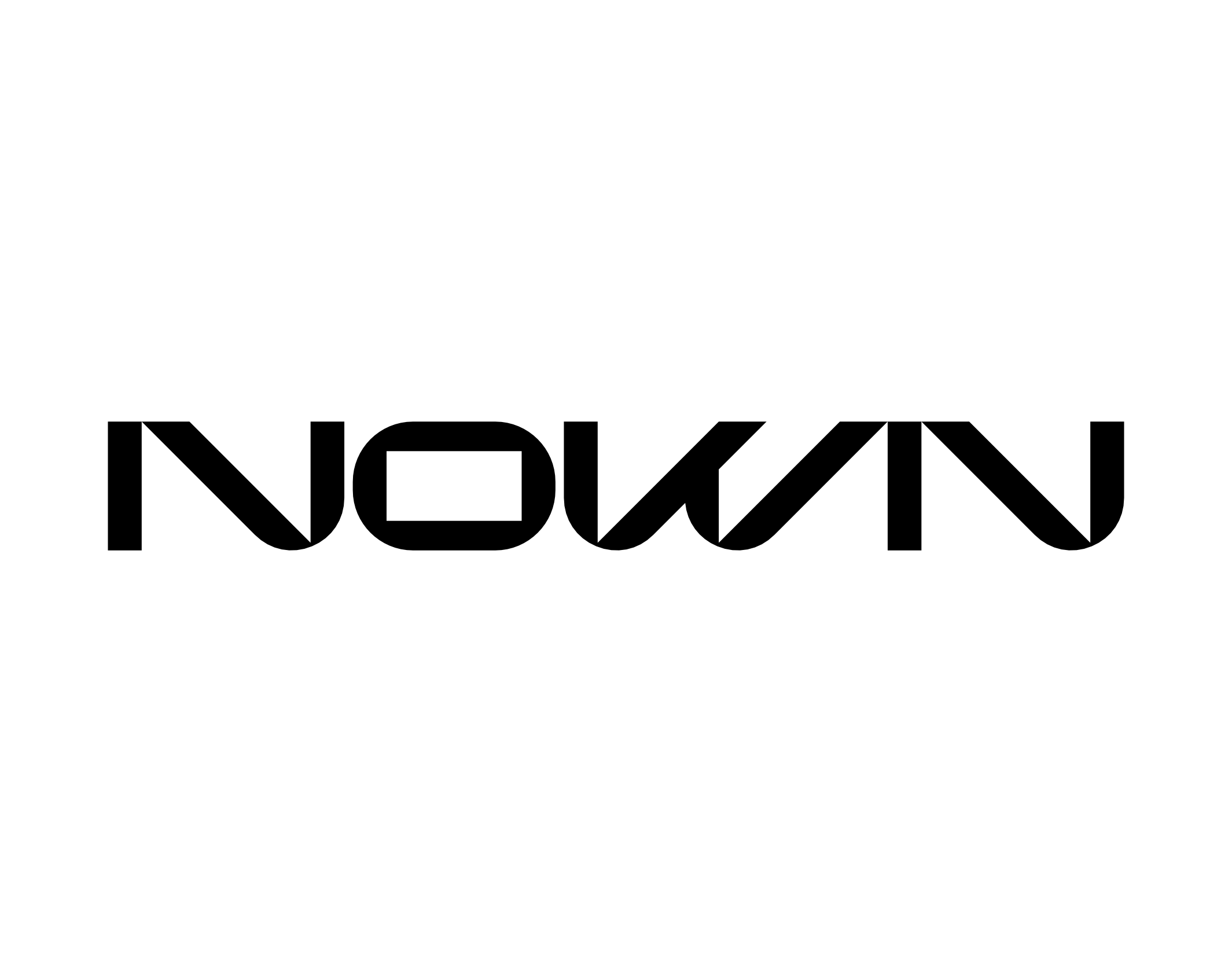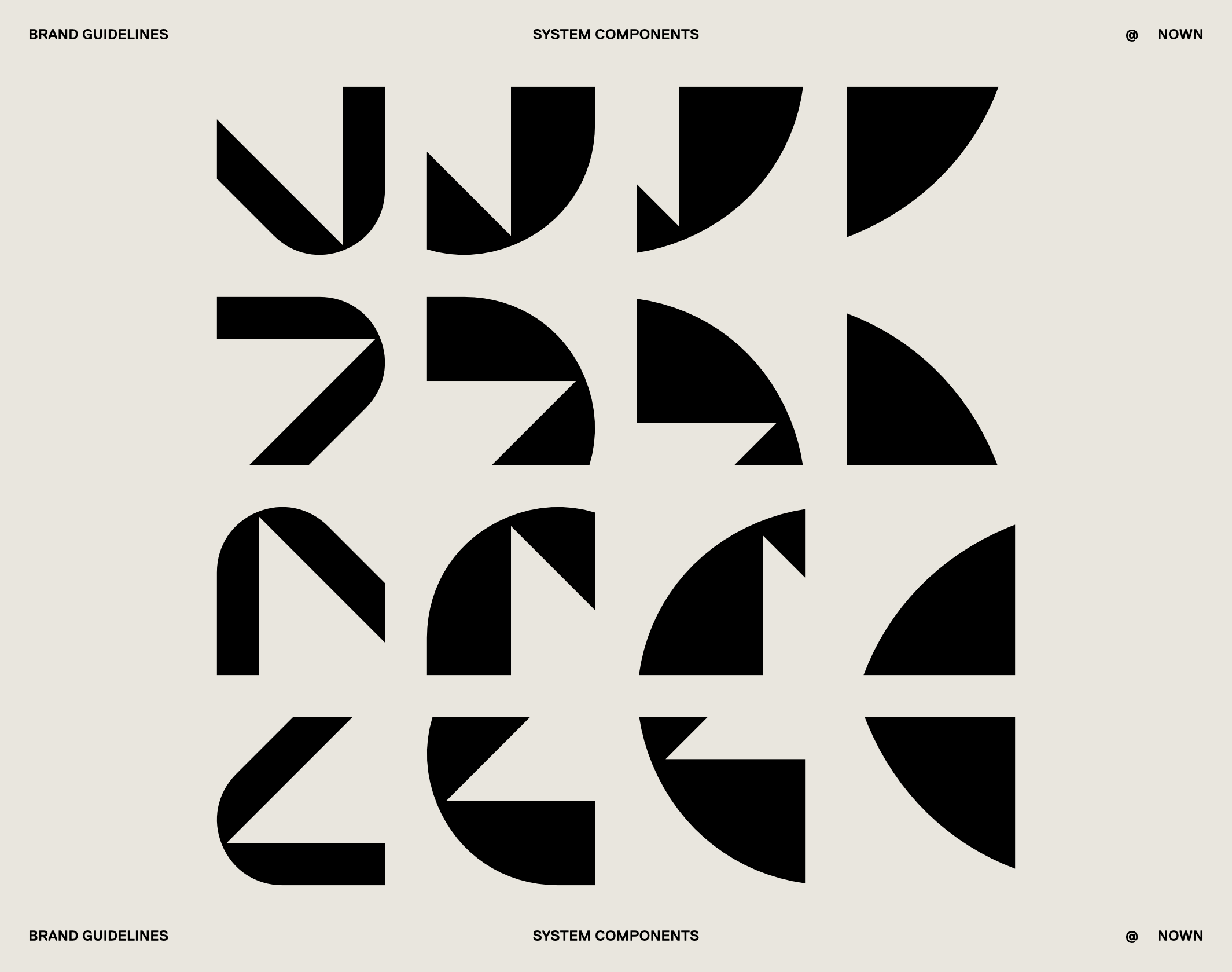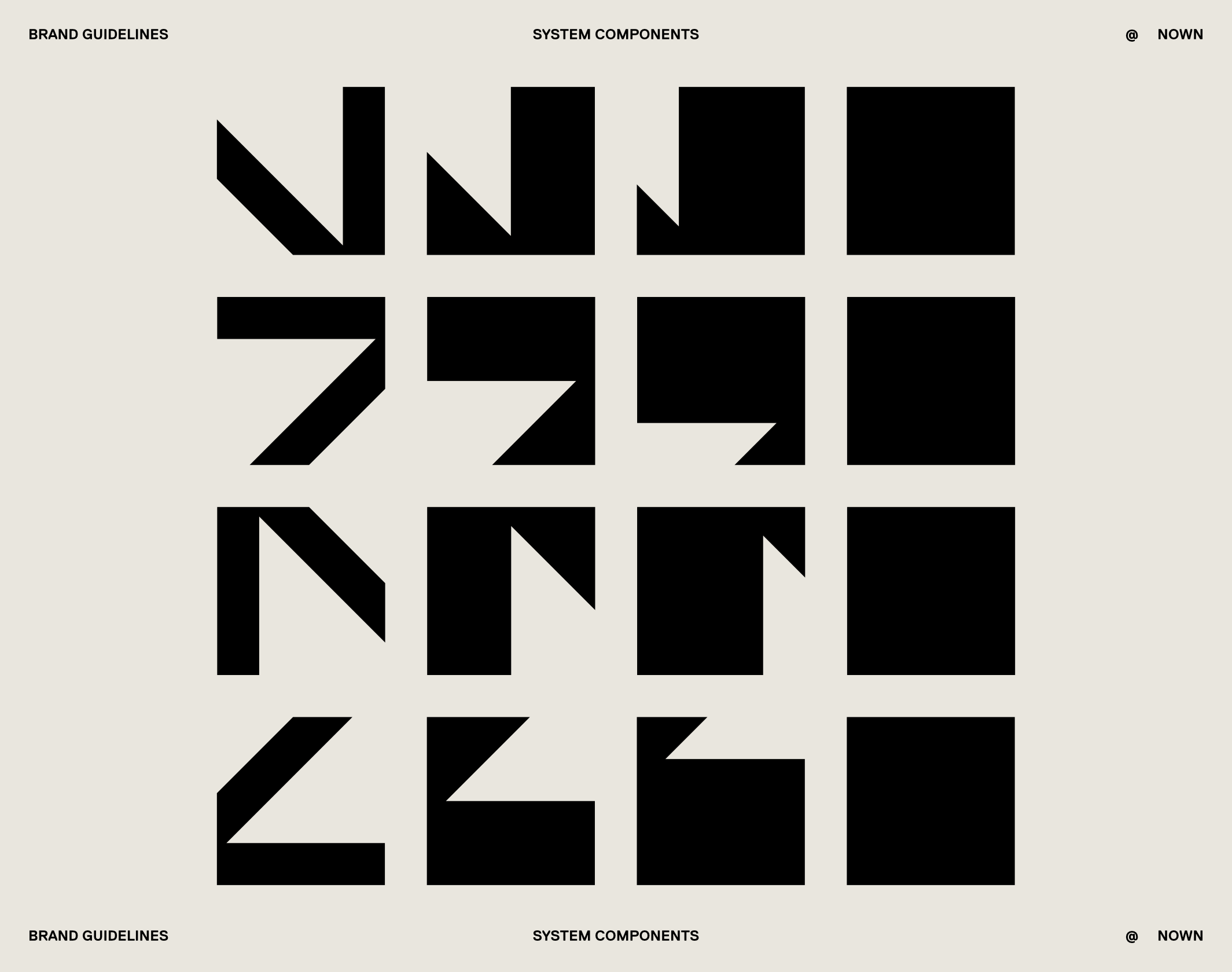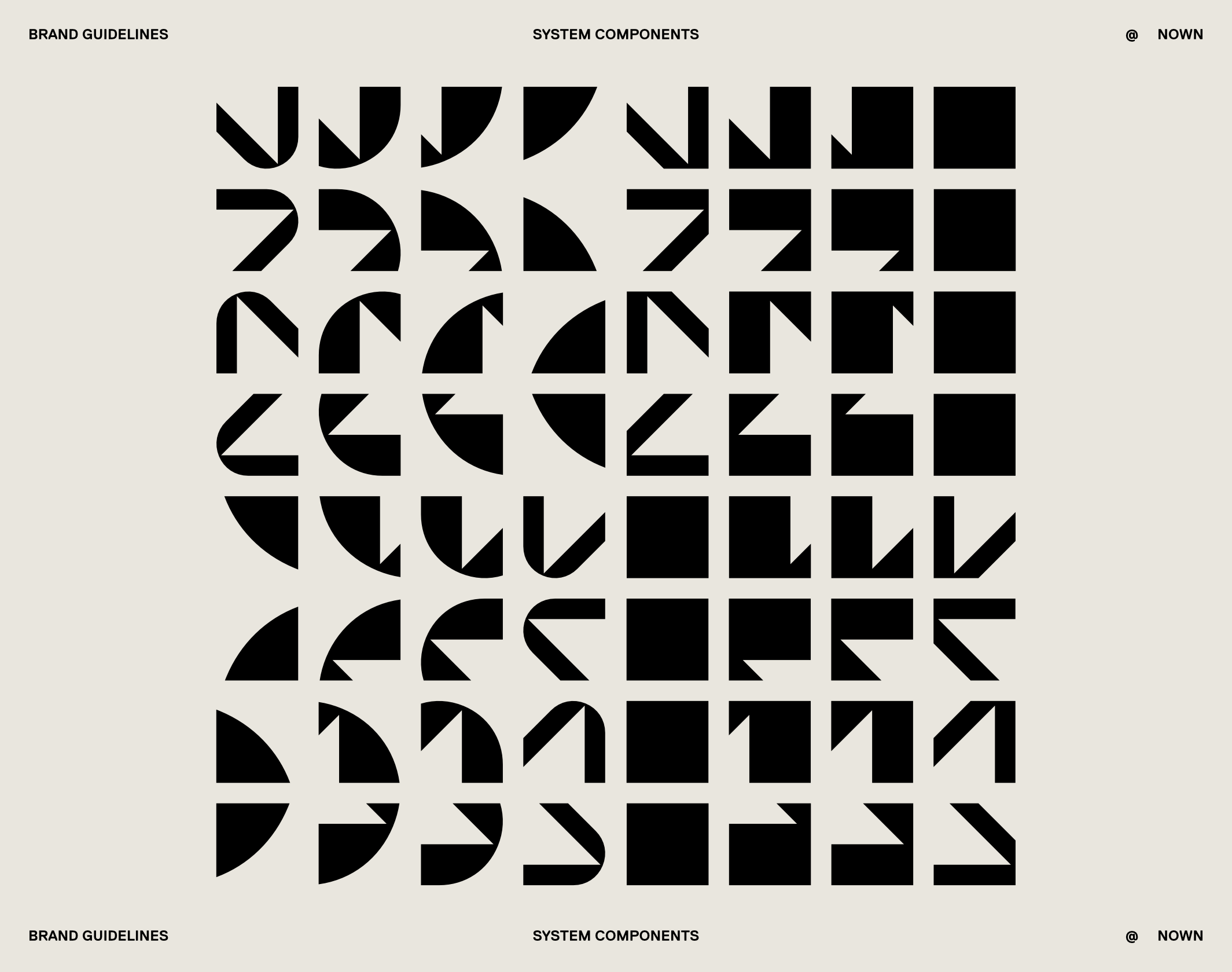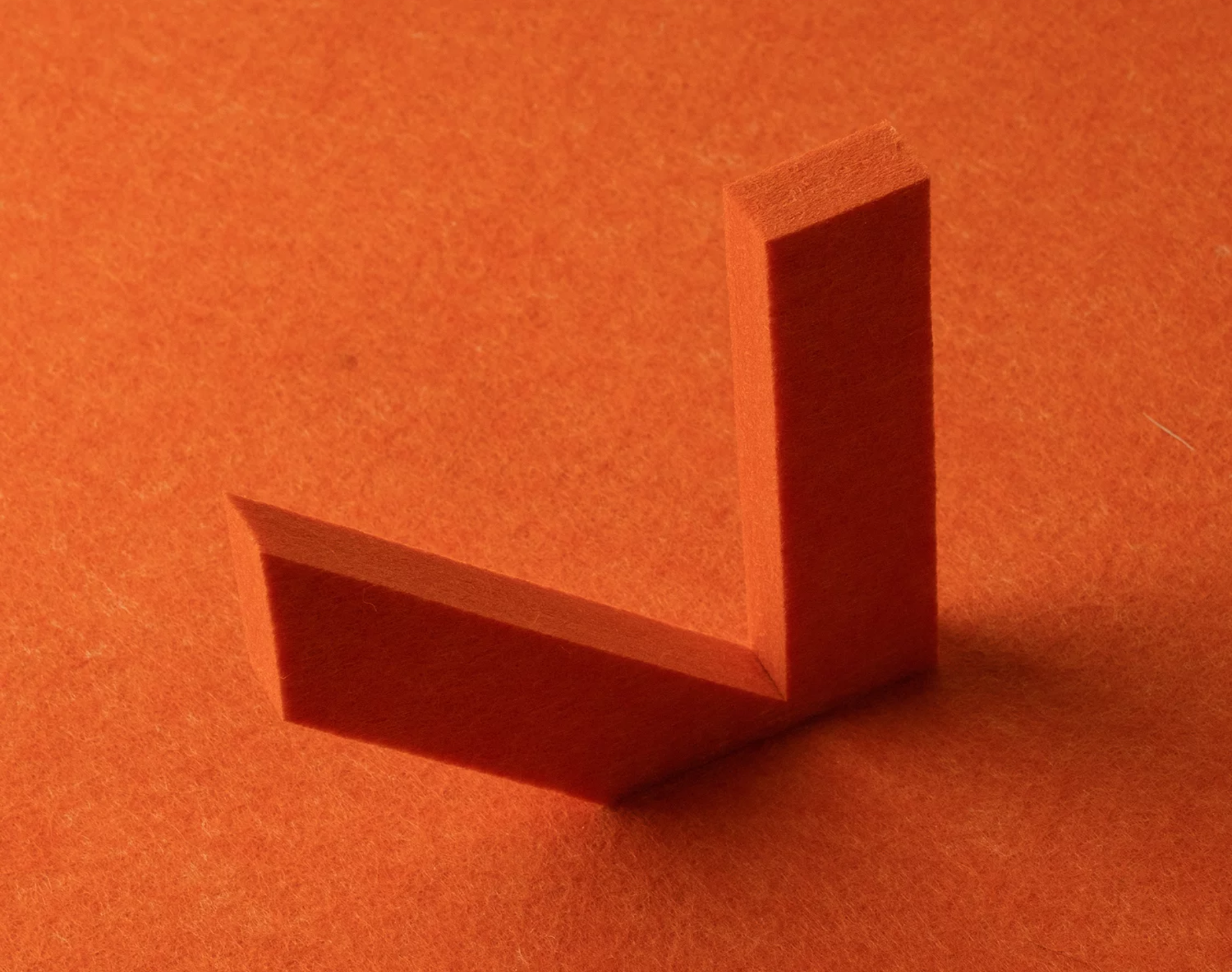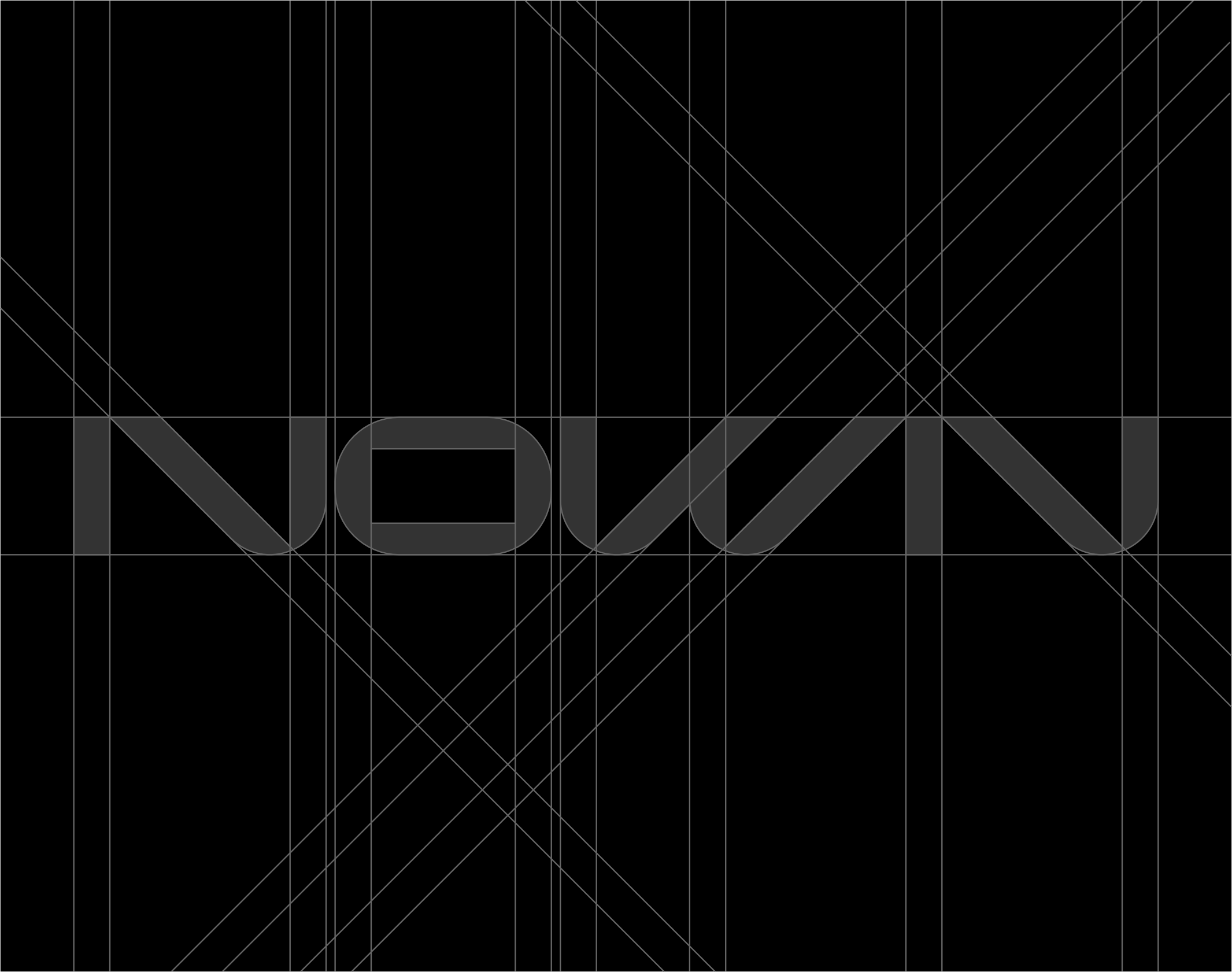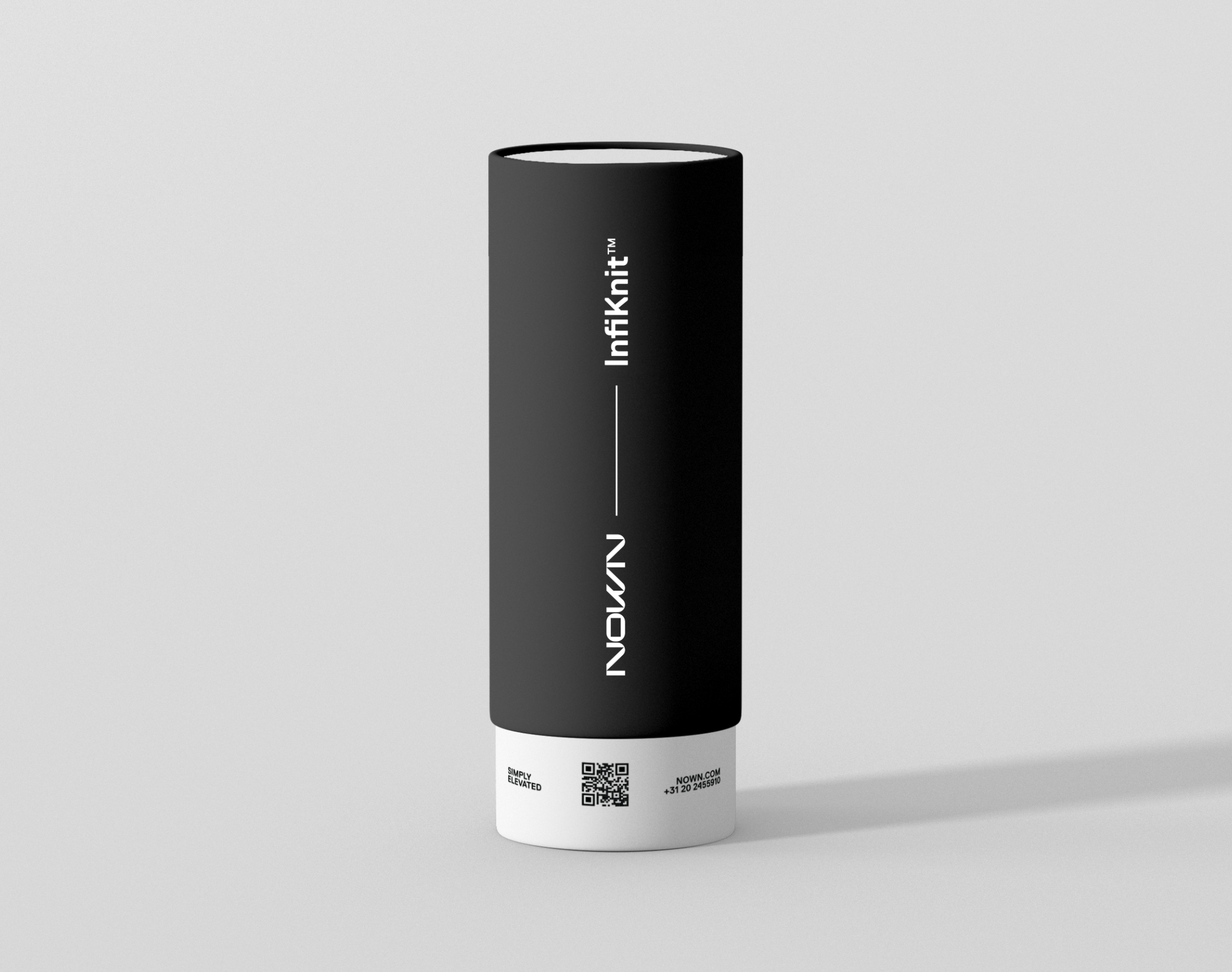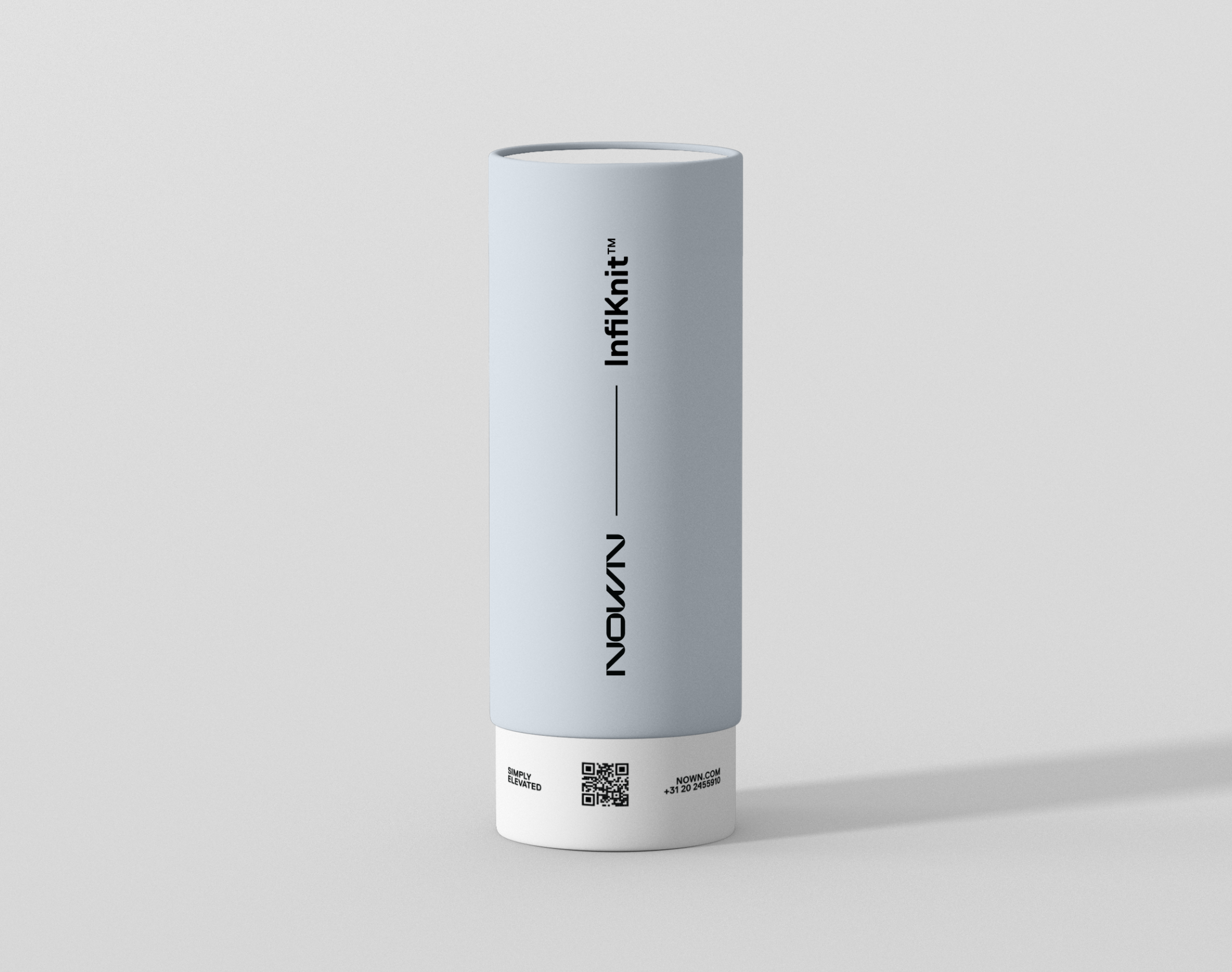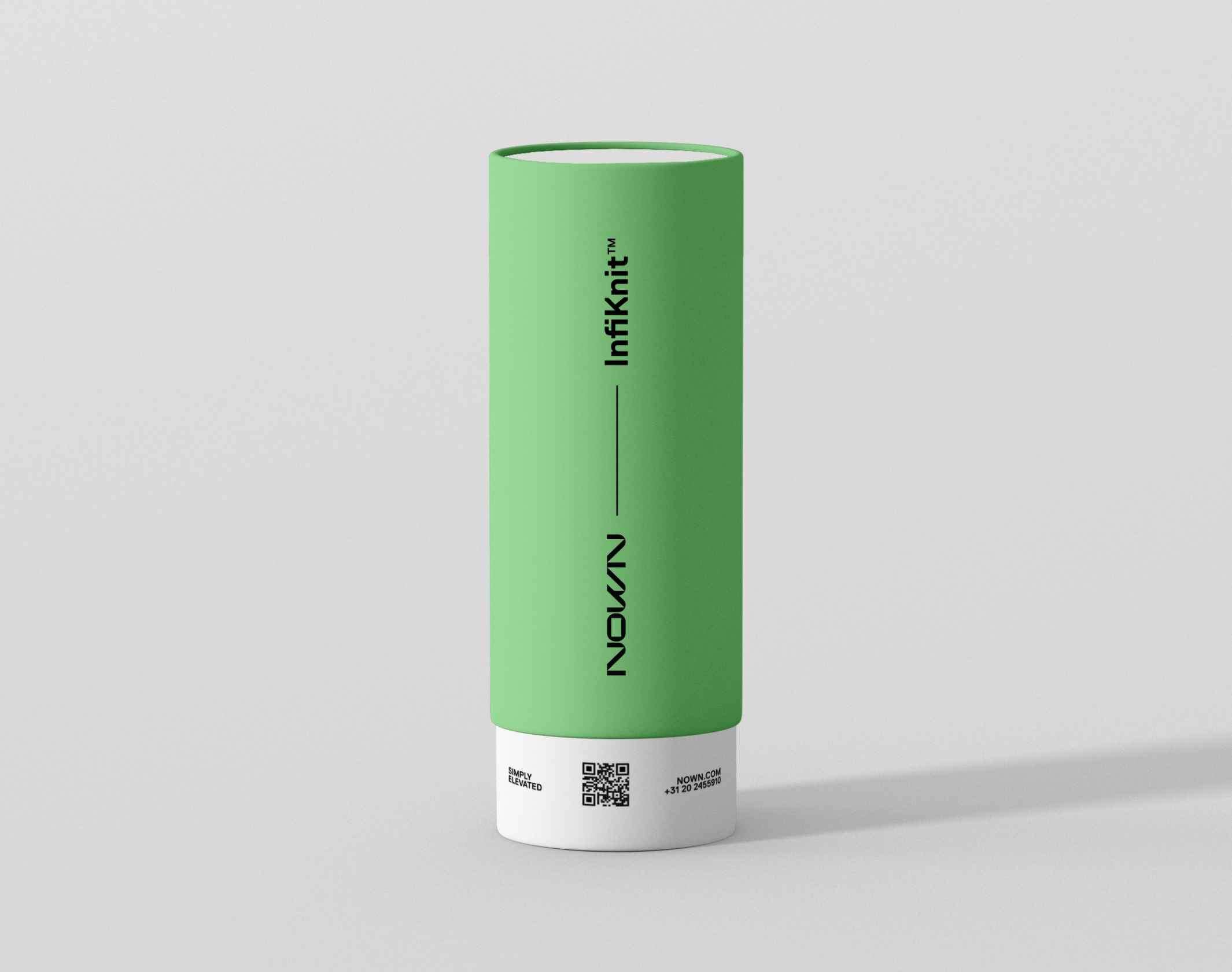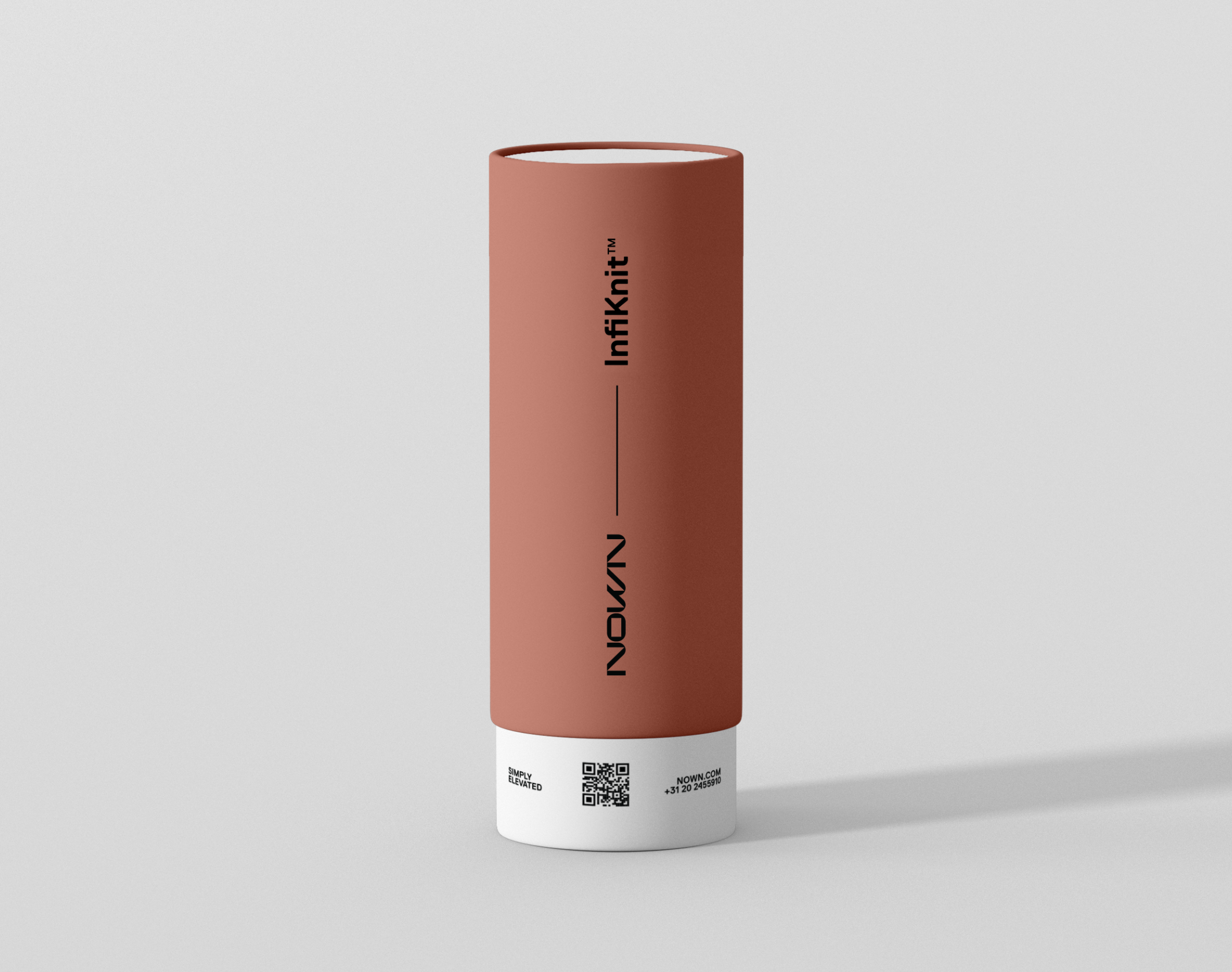
Nown
Nown, pionnier des produits architecturaux neutres en carbone, se distingue par une identité visuelle innovante alliant design et précision.
Nown (ex-Arktura EMEA), est un groupe composés d’architectes, designers, de programmeurs, ingénieurs et artistes basé à Amsterdam, et se revendique comme étant le premier fabricant de produits architecturaux neutres en carbone. Spécialisés dans le design en élévation, l’entreprise produit des plafonniers, panneaux mureaux, cloisons et baffles acoustiques, à l’installation facile, 100% neutres en carbone et au design primé. Véritables expérimentateurs de l’espace et de la forme, les équipes Nown produisent intégralement sur leur site d’Amsterdam, avec des standards de qualité et une obsession du détail qui ont fait leur réputation à travers le monde.
Brand Brothers a été chargé de créer intégralement l’identité visuelle de Nown, avec pour mission de raconter l’élévation, la précision et l’obsession du beau par la typographie et un système graphique complet. Le nouveau typogramme est un dessin 100% custom, rythmé par une découpe franche, des angles répétitifs et des points de rencontre précis entre les segments. Il se dégage ainsi un objet graphique précieux, à la frontière du design et de l’ingéniérie. Le système graphique s’articule autour de l’angle pivot des caractères pour former une série de composants qui viennent raconter les produits Nown par l’abstraction, mais aussi la modularité et la simplicité d’utilisation. Une palette de couleurs étendue et une utilisation méthodique du caractère Replica (par Norm, édité par Lineto) parachèvent l’élaboration d’un branding expérimental mais sophistiqué, conçu pour durer.